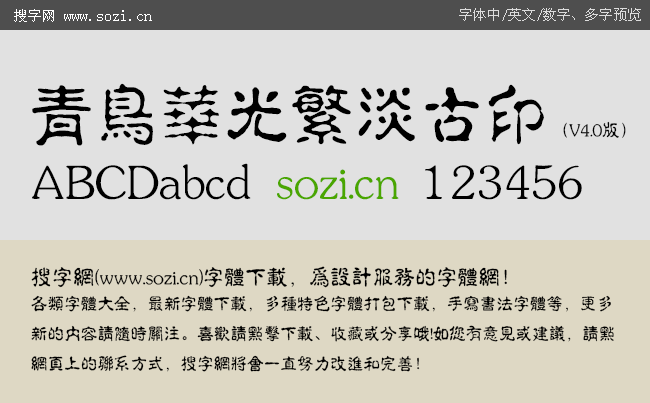
青鳥華光繁淡古印
搜字網(wǎng)給大家提供一款青鳥華光繁淡古印中文藝術(shù)字體下載。青鳥華光繁淡古印是一款設(shè)計(jì)非常復(fù)古具有獨(dú)特韻味的字體,青鳥華光繁淡古印圓潤、美觀,可用畫冊設(shè)計(jì)、平面設(shè)計(jì)、印刷包裝、報(bào)紙雜志等廣告設(shè)計(jì)場合使用。
• 風(fēng)格類別: 古印體